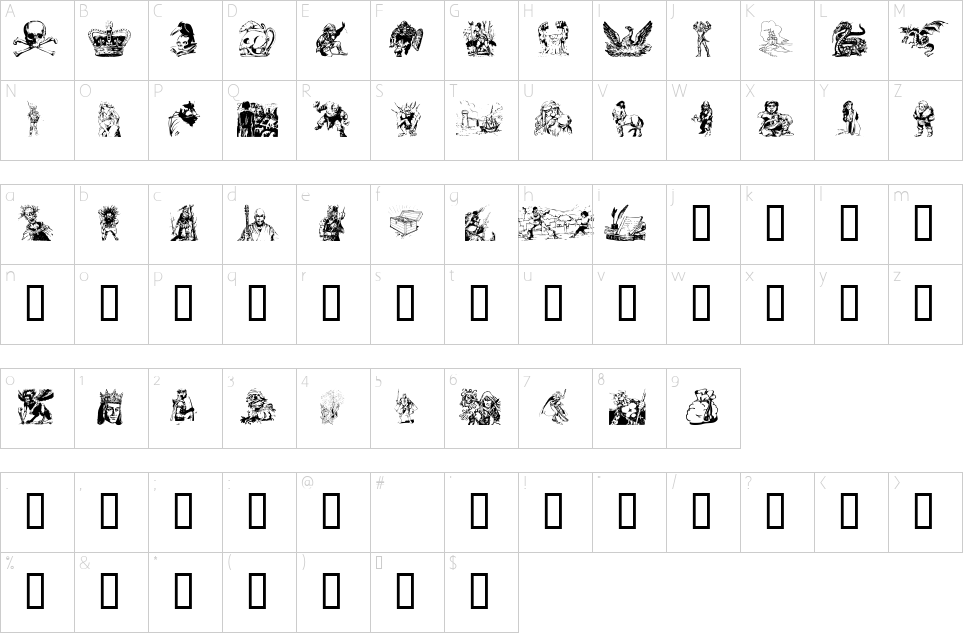
A Fantasy Clipart 1 é uma fonte que combina elementos de fantasia e arte gráfica. Seu design é simples e envolvente, ideal para criar designs interessantes e único. Esta fonte foi criada pela equipe da Gem Fonts e já foi baixada mais de 151,781 vezes. Se você está procurando por uma fonte com um pouco mais de personalidade e um toque de fantasia para suas criações, a Fantasy Clipart 1 é uma boa escolha. Ideal para designers de logotipos, designers gráficos e até mesmo criadores de arte digital, esta fonte oferece um toque especial que pode transformar qualquer projeto. Aproveite a sua descarga e experimente esta fonte para criar algo realmente especial.